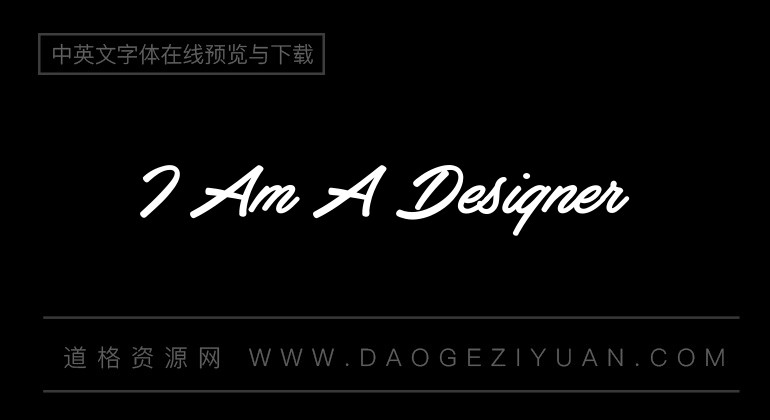
? I Am A Designer 字体是一款设计师专用的字体,由著名设计师Randy Ford亲自设计,它拥有一种独特的外观,具有清晰的英文字体,以及多种不同的符号和图形,可以满足设计师的各种需求。它具有优秀的可读性,能够更加清晰地表达设计师的创意,并且也能够帮助设计师更好地完成他们的工作。内容介绍
I Am A Designer是一款非常不错的手写艺术字体,具有很好的视觉感,适合于文化类的宣传设计、商业类品牌的广告和产品包装设计以及个性化文字排版等较多场景。